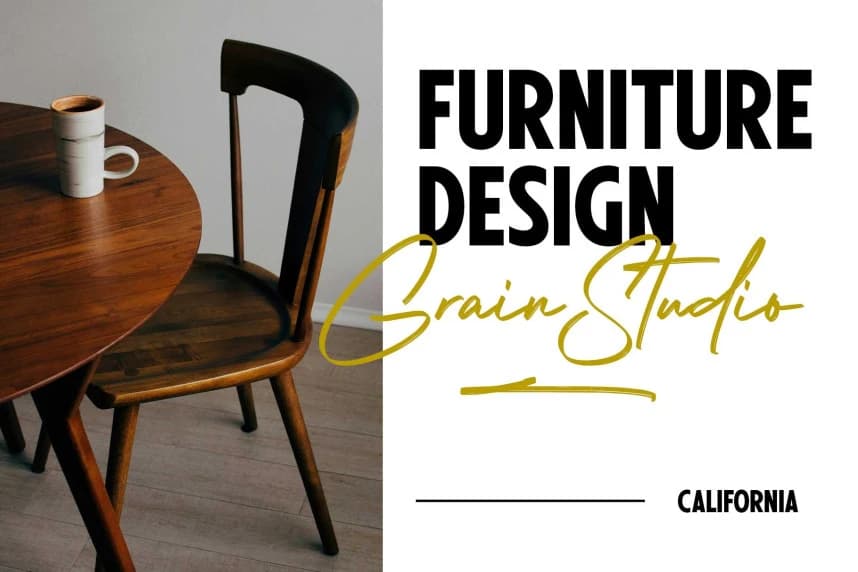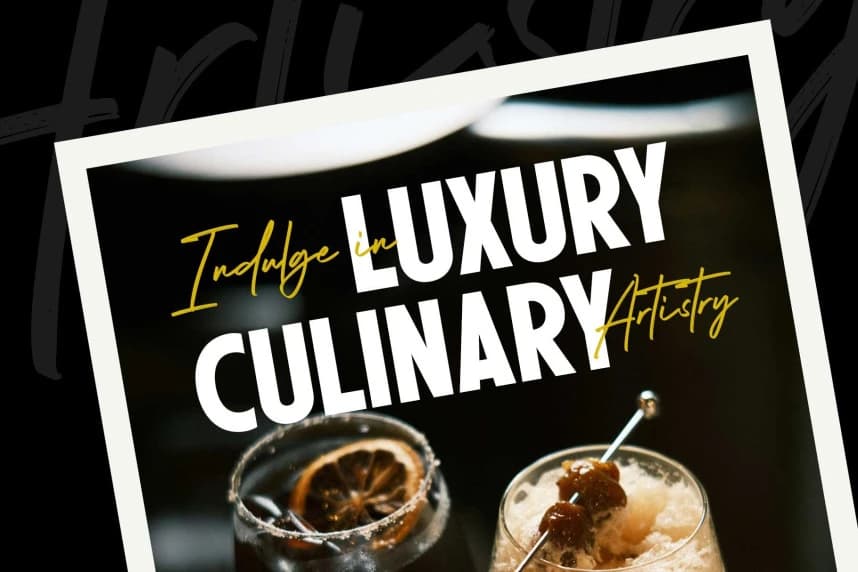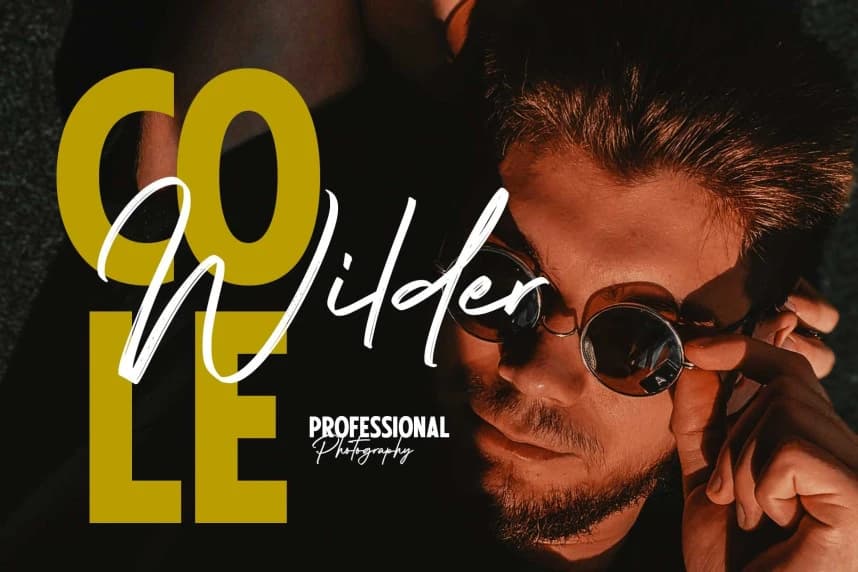
Shelvia Montanila Font Duo
Shelvia Montanila Font, cesur netlik ile ifadeli zarafetin buluştuğu güzel bir font ikilisi. Bu eşleşme, güçlü, modern bir sans serif ile akıcı bir imza yazı tipinin birleşimini sunar—yapı ile kişiliğin mükemmel dengesini yaratır.
Shelvia Montanila Font, kalın netliğin ifade dolu zarafetiyle buluştuğu güzel bir yazı tipi ikilisi. Bu eşleşme, güçlü ve modern bir sans serif ile akıcı bir imza yazısı arasında dengeli bir uyum sağlayarak yapı ile kişiliğin mükemmel dengesini yaratır.